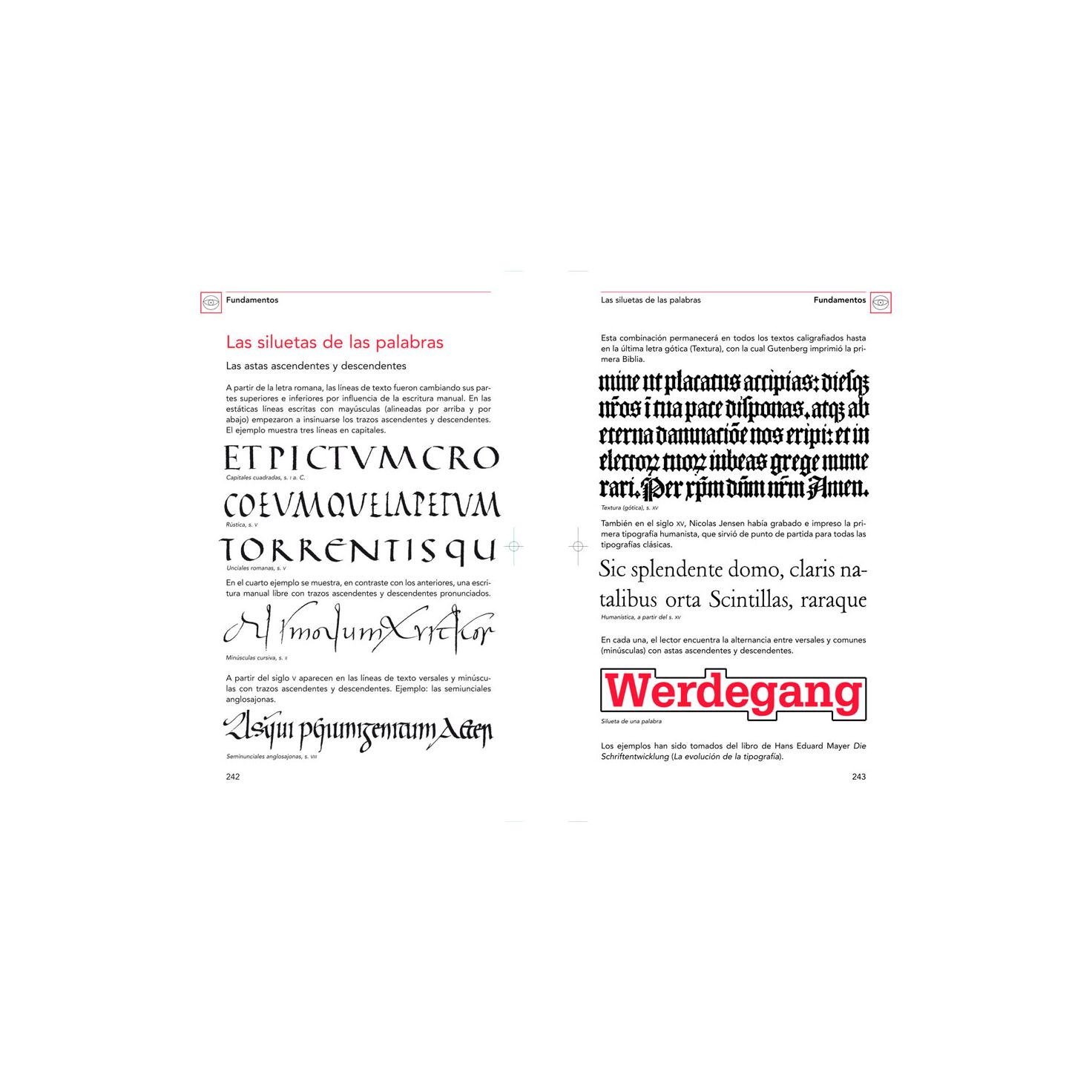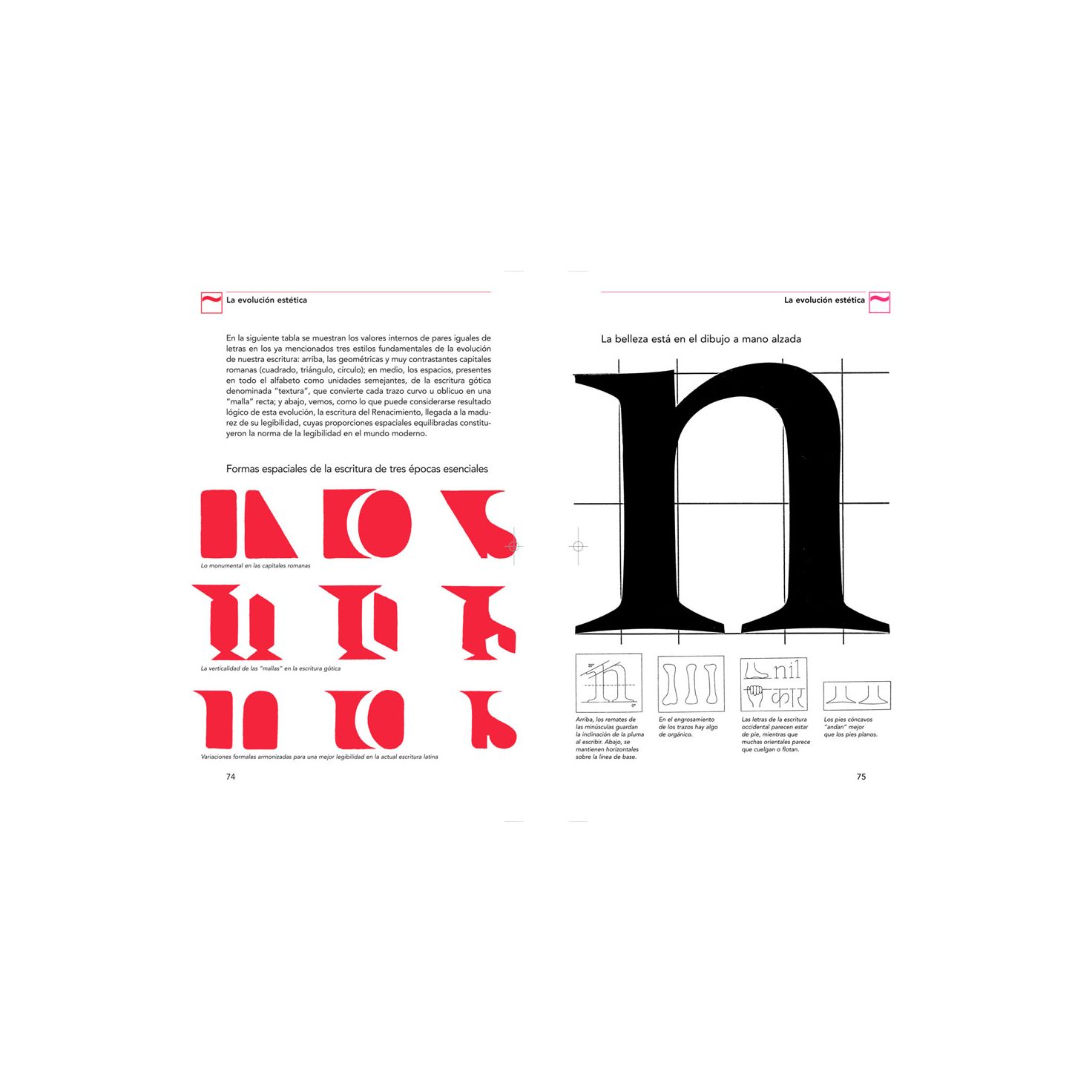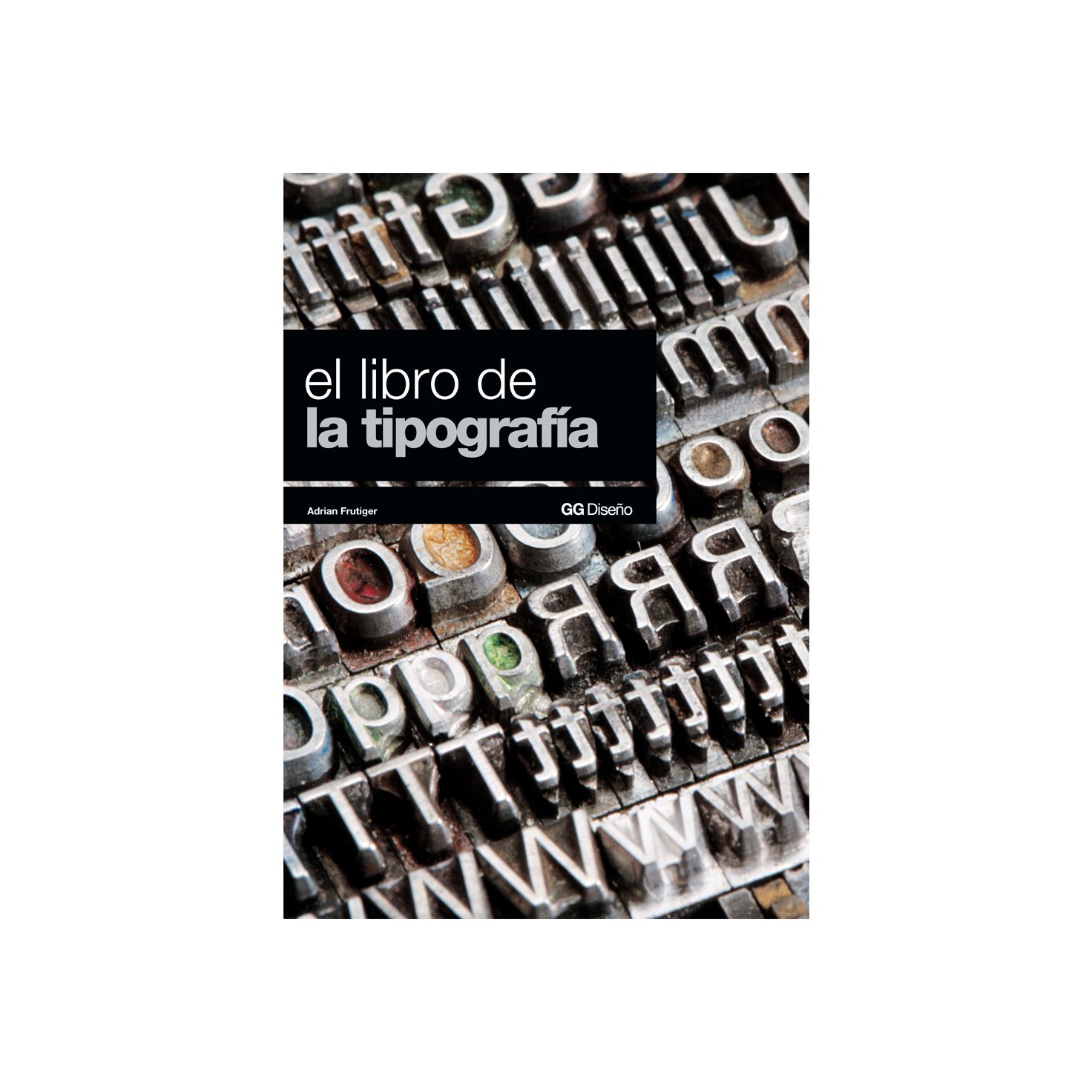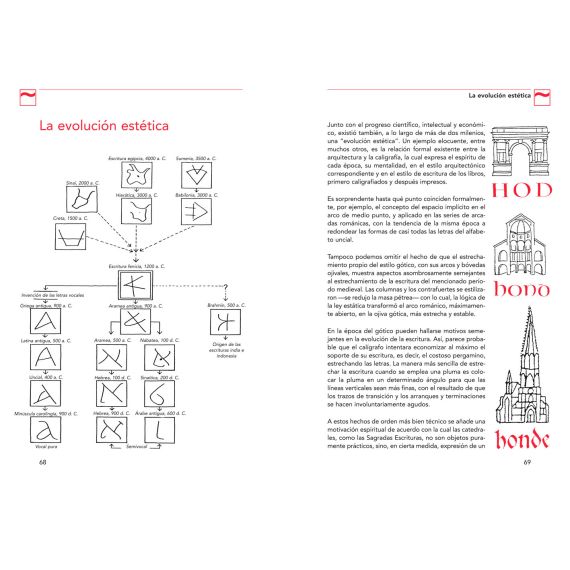
El libro de la tipografía
'Una tipografía debe estar diseñada de tal manera que nadie repare en ella.'
Tras la aparente simplicidad de esta afirmación de Adrian Frutiger se esconden varios decenios dedicados al diseño de tipografías y al estudio de la forma en que los seres humanos interactúan con ellas. Frutiger se niega a concebir la tipografía como un fin en sí mismo, apuesta por subordinar el diseño a su finalidad práctica de servicio a las personas y defiende que el máximo logro al que puede aspirar el diseñador de tipos es que su tipografía pase desapercibida en su lectura.
La tipografía debe estar adaptada a su contexto: 'Las líneas grises de la página de un libro se leen de distinta manera que las letras de una señalización. Hay una enorme diferencia entre leer tranquilamente sentado en el sillón y esperar estresado a embarcar en un avión. En cualquiera de estas situaciones el lector debe sentirse cómodo. Desde ese convencimiento Frutiger exhorta a los jóvenes diseñadores a no dejarse guiar sólo por la creatividad o las modas, sino también por las circunstancias, es decir, por la finalidad de la tipografía y por el entorno en que ésta ha de figurar.
La larga experiencia de Adrian Frutiger se convierte en estas páginas en un material de incalculable valor tanto para los diseñadores como para los profanos que se acercan con curiosidad a este tema.